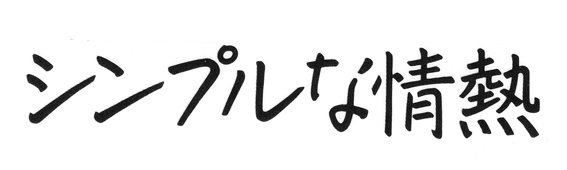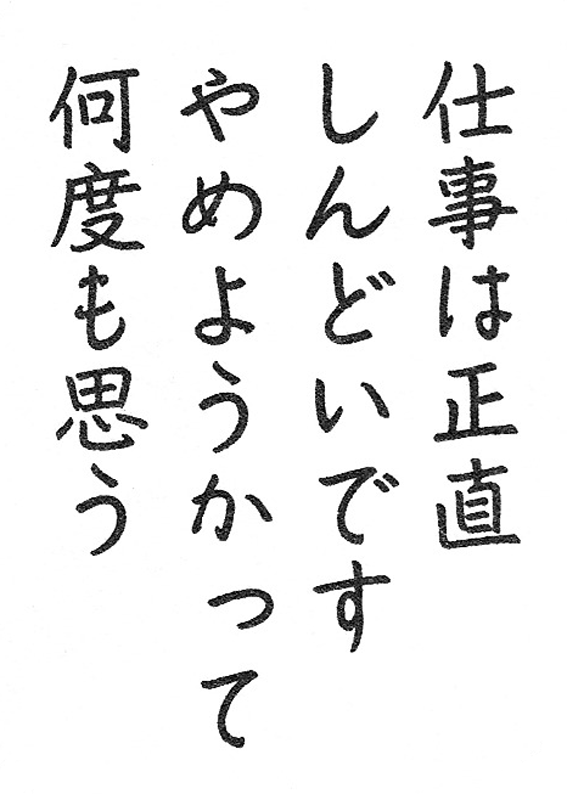
ナカフリー
この文字は、白い。
文字の印象が「白」だなんて、妙なことをいう、と思われるかもしれない。
「白」は「無」をイメージさせる色でもあるけれど、この場合、味がしない、という意味では決してない。文字の背景にある白い部分が、線に隔てられることによって際立ち、よりいっそう映えるような感じ。
私はその「白さ」が好きだ。何もないところに文字がかかれるということは、結局、その白さをいかように残すか、ということだともいえる。
文字の白。線と線のあいだに透けてみえる白。
それはヨーグルトの白さに、すこし似ている。乳清、と呼ばれる上澄みの部分に栄養があるのだと、だから残さずにすくって食べなさい、と、子どものころにいわれた。あの、淡泊で、ぽってりとした白さ。仄かに酸っぱい風味もする。
あのころ、とにかく印象的だったのは、この書体の滑らかさだ。生理的で、すべすべしたクリームみたい。
書体に性別があるとしたら、間違いなく〈ナカフリー〉は女性だ。長いあいだそう信じて疑わなかったのだが、この書体は、前出の中村征宏氏が「ふだん妻がかいていた文字を、大きさや中心が揃うようにデッサンし直して」つくったものだという。
あのきわめて男性的な〈ゴナ〉と、〈ナカフリー〉が、同じデザイナーの手によるものだ、というのはにわかに信じがたいけれど、そのエピソードを知った後では、すごく納得のいくことのようにも思える。
というのは、〈ナカフリー〉の「女性らしさ」は、まったく媚びを含んでいないというか、どこか母性的な感じがするからだ。健やかで、シンプルで、やわらかい。
つくづくユニークだなあと思うのは、書体のイメージが、ときに倒錯した状況で――もちろん計算された演出のもとに――言葉と結びつくことだ。そんなとき、文字は、得体の知れない可笑しみをもたらす。
〈ナカフリー〉は、手紙文でよくつかわれる写植書体である。
手紙形式の文章には教科書体も好まれるけれど、〈ナカフリー〉は、教科書体よりかしこまっていなくて、人目につくことを想定していない感じというか、プライベートを直にのぞきみるような気配が漂う。
でも、たとえば、謎の組織から届いた秘密文書とか、身に覚えのない果たし状(もらったことはないけど)とかには、この書体は到底似合わない。
本を読んでいて、この文字でかかれた「手紙」が出てくると、私は、ああ、よく知っているひとからの手紙だ、と思う。名前をみなくてもわかる文字。
どうしてだろう。
実際のところ、自分の身近に、これと似た文字をかくひとはいないのに。それなのに、どういうわけか、私はこの文字に対して自然と好意をもっていたし、一緒に朝ごはんを食べる相手みたいな親しさを抱く。
「働きマン」で〈ナカフリー〉がつかわれているシーンも私はすごく好きだ。
初めて読んだとき、この台詞は手紙だ、と思った。どこにも届くはずのない、出されなかった手紙。
そう感じたとき、自分とは別の世界に生きているはずだった登場人物たちは、すでに親しい、近しい存在になっていた。
文字の印象が、限定されたなつかしさを呼び覚ますからかもしれない。
そのひとの文字を知っている、と思えることほど、シンプルに心の距離をはかる基準もないと思う。
「あなたがかいた文字をみれば、私はすぐにわかります」
そんなことを普段わざわざひとに伝えたことはないけれど、口に出してみると、まるで恋心をうちあけるみたいで恥ずかしい。
他人の筆跡を思いだすだけでそうなのだから、好きなひとの文字を「まねする」のは、究極の愛情表現だよなあ。
と、思うのですが、どうでしょう?